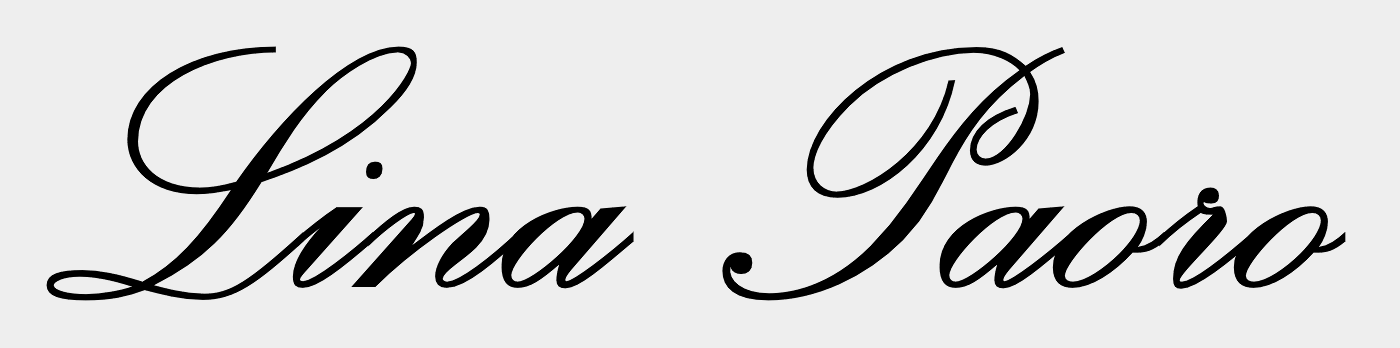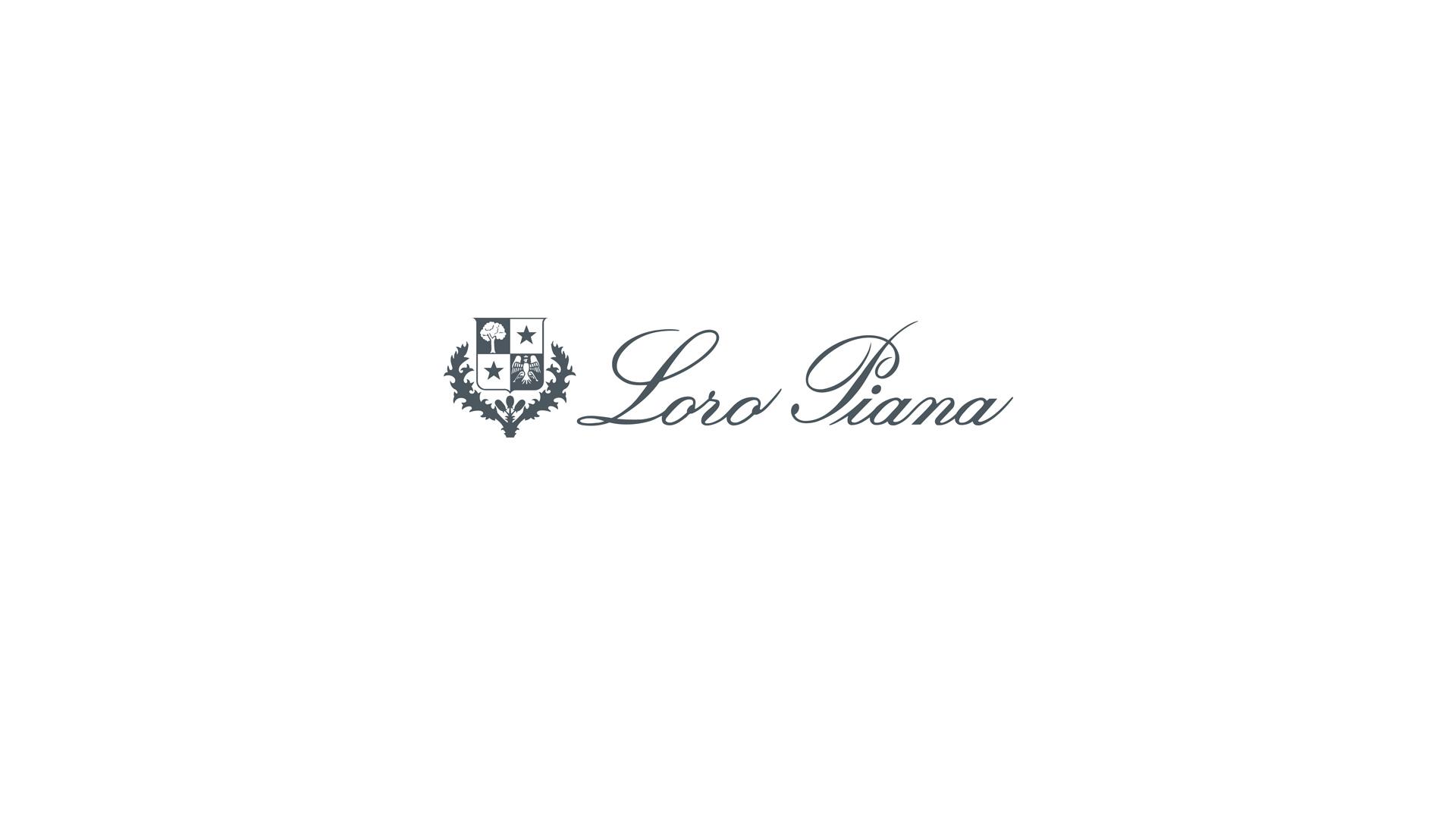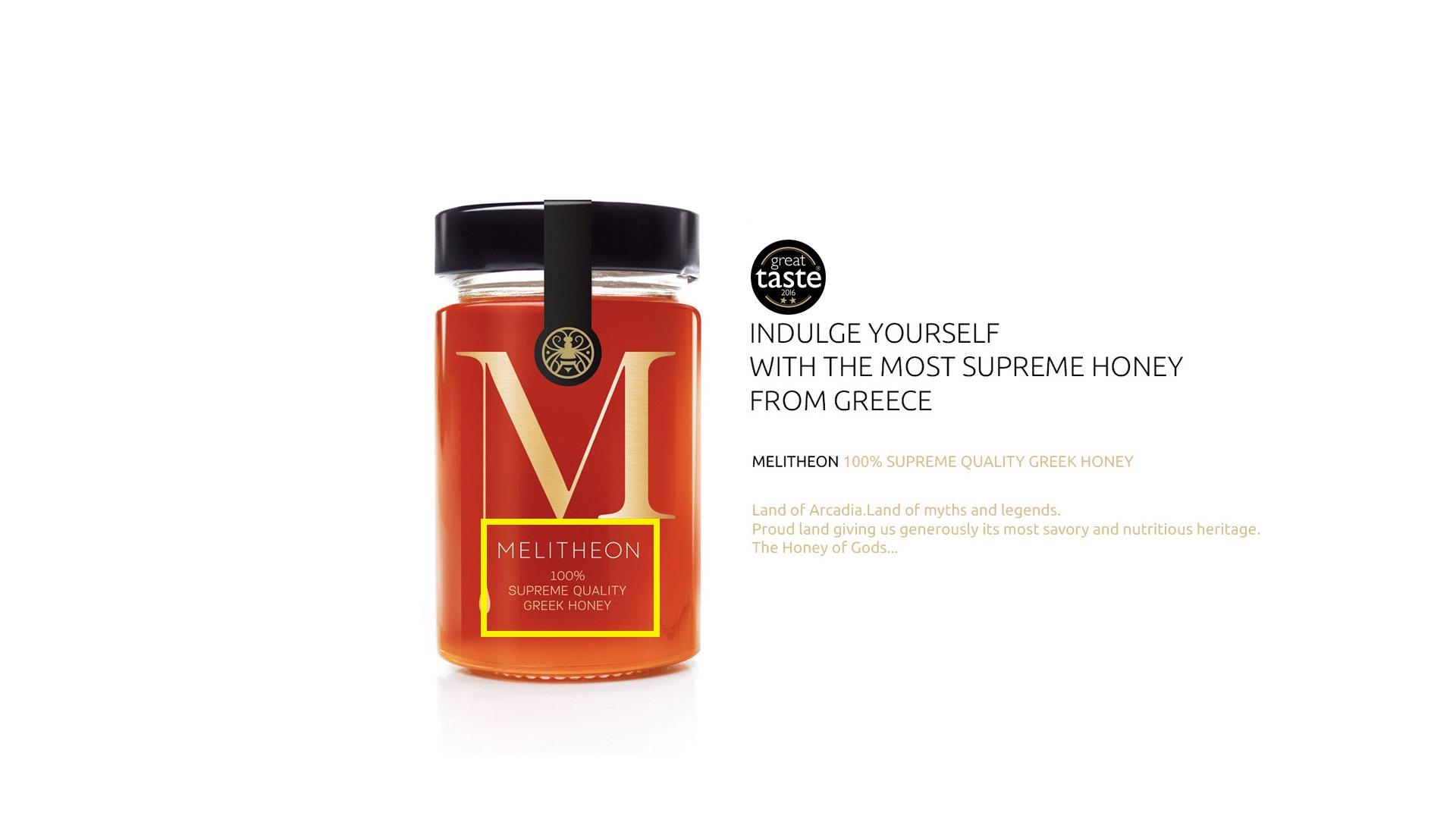
[Mitglied 3025…] Geschrieben Dezember 2, 2019 Teilen Geschrieben Dezember 2, 2019 Hallo ihr Lieben, ich suche diese eleganten Schriftarten von Loro Piana und Melitheon. Sollte jemand auch andere Schriftarten kennen die ebenfalls sehr Elegant und Stilvoll sind, dann bitte mich darüber informieren. Danke und viele Grüße, Area51 Link zu diesem Kommentar
[Mitglied Mart…] Geschrieben Dezember 2, 2019 Teilen Geschrieben Dezember 2, 2019 Die Schrift des MELITHEON-Logos wurde hier schon mal gesucht (und gefunden). Link zu diesem Kommentar
[Mitglied R::b…] Geschrieben Dezember 2, 2019 Teilen Geschrieben Dezember 2, 2019 vor einer Stunde schrieb Area51: Sollte jemand auch andere Schriftarten kennen die ebenfalls sehr Elegant und Stilvoll sind, dann bitte mich darüber informieren. Deiner Suchanfrage folgend: Link zu diesem Kommentar
[Mitglied 3025…] Geschrieben Dezember 2, 2019 Teilen Geschrieben Dezember 2, 2019 Danke, jetzt fehlt nur noch die Schriftart von Loro Piana. Link zu diesem Kommentar
[Mitglied D2C…] Geschrieben Dezember 2, 2019 Teilen Geschrieben Dezember 2, 2019 Hallo @Area51, wozu suchst du die Schriften denn? Für mich kommt der Logotype von Loro Piana die Palace Script (Stephenson Blake, 1923) am nächsten. In den Details stimmt sie aber auch noch nicht. Entweder wurde die Palace Script für die Logotype individuell bearbeitet oder aber es handelt sich um eine andere Schrift, die auf dieselbe Quelle wie die Palace Script zurückgeht – anscheinend einen Entwurf von Deberny & Peignot aus den 1880er-Jahren. Ich weiß nicht, wie lange das hier gezeigte Logo schon im Einsatz ist, aber die Firmengeschichte von Loro Piana selbst reicht ja auch bis ins 19. Jahrhundert zurück. bei MyFonts herunterladen 1 Link zu diesem Kommentar
Beste Antwort [Mitglied 3025…] Geschrieben Dezember 2, 2019 Beste Antwort Teilen Geschrieben Dezember 2, 2019 Die Zusammenfassung: MELITHEON-Logo = Neutraface No. 2 von House Industries Loro Piana-Logo = Palace Script von Monotype Link zu diesem Kommentar